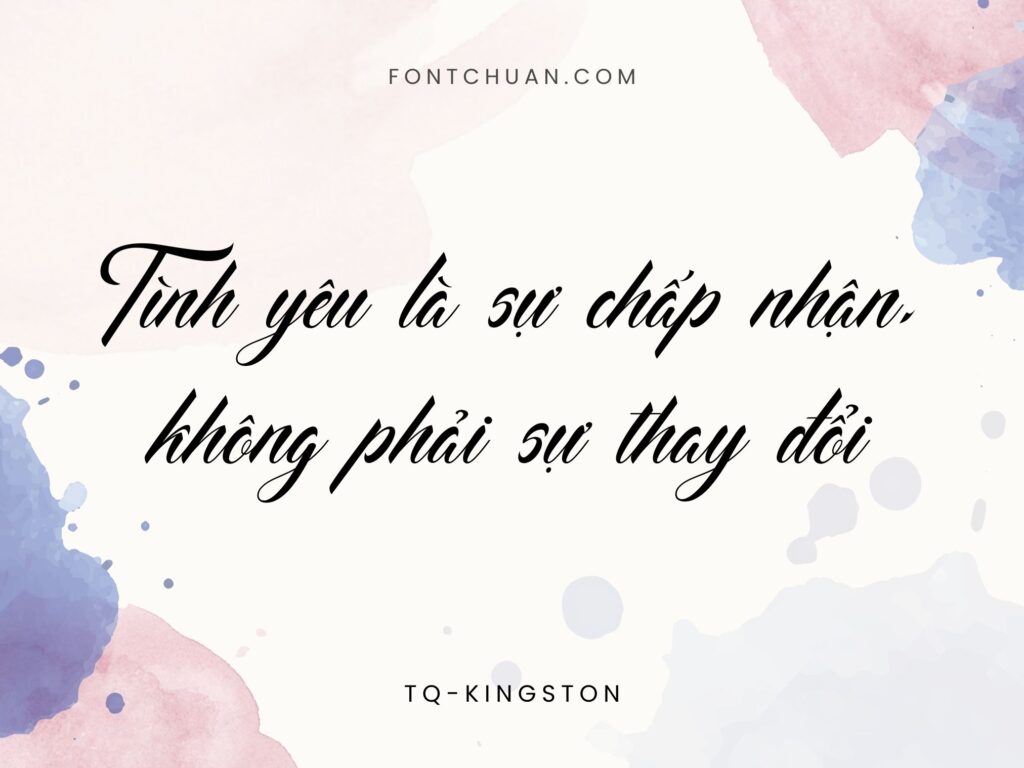
Font Tq Kingston Việt Hóa
Tác giả Font: Thr Type
Việt hóa bởi: Thúy Quỳnh
TQ-Kingston là phiên bản Việt hóa của font Kingston, một kiểu chữ script được thiết kế bởi Staircase Studio. Font này mang phong cách viết tay tự nhiên với các nét chữ mềm mại và uyển chuyển, tạo cảm giác thanh lịch và hiện đại. Phiên bản Việt hóa được thực hiện bởi Thuý Quỳnh, hỗ trợ đầy đủ tiếng Việt và nhiều ngôn ngữ khác. Font được sưu tầm và đăng bởi thành viên của Font Chuẩn.
Font có thiết kế chữ viết tay với độ nghiêng nhẹ, các đường nét mượt mà và tinh tế, phù hợp cho các thiết kế như thiệp mời, logo, tiêu đề và các ấn phẩm truyền thông cần sự sang trọng và cá nhân hóa. Các ngành nghề như quảng cáo, thiệp cưới, giáo dục và ẩm thực có thể tận dụng hiệu quả font này. Ngoài ra, cho những thiết kế mang không khí lễ hội, vui nhộn, Font chữ Halloween này là lựa chọn hoàn hảo với các họa tiết đặc trưng như mạng nhện, dơi và bóng ma, tạo điểm nhấn sôi động cho các sự kiện như lễ hội, sinh nhật, ngày Nhà giáo và Valentine.